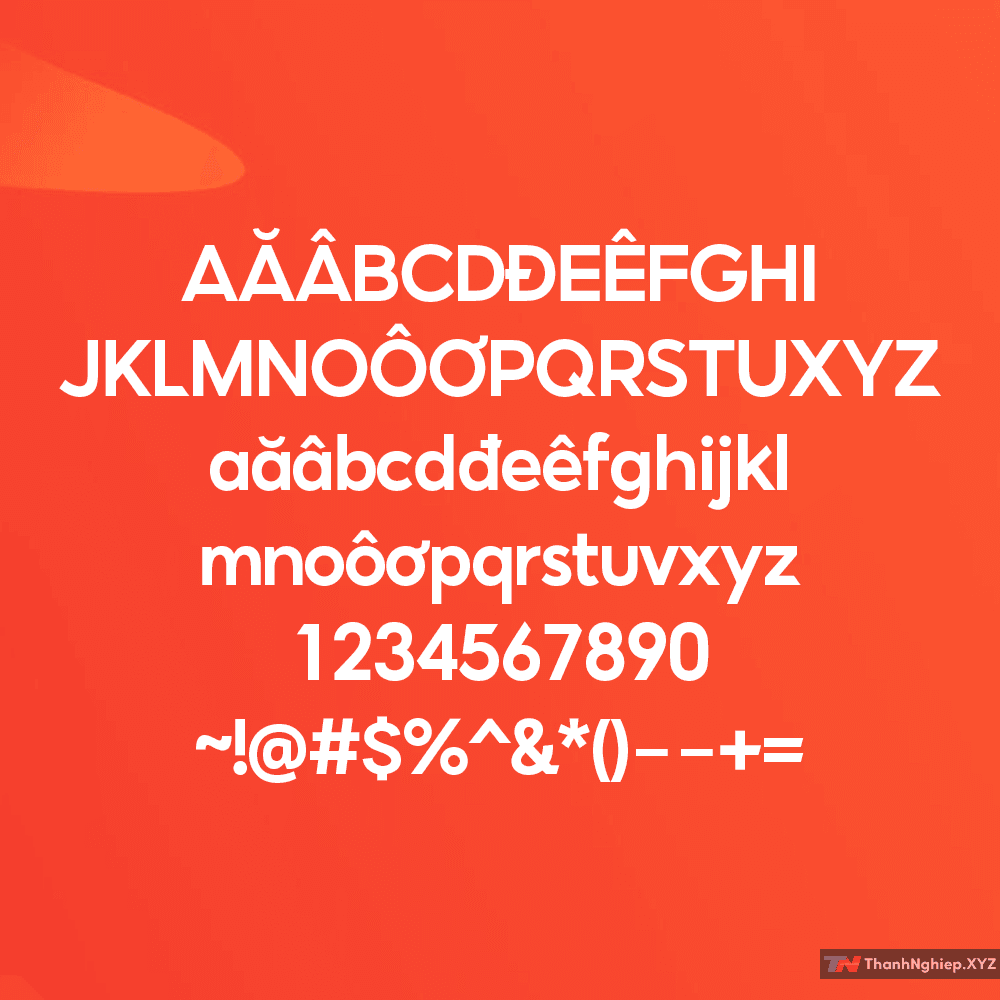
Bạn có bao giờ lướt Shopee và tự hỏi: “Ủa, sao font chữ trên app nhìn bắt mắt dữ vậy ta?” Bí mật chính là bộ Shopee Display & FVH Shopee Text – một combo font cực chất, giúp mọi thiết kế của bạn trông chuyên nghiệp, hiện đại và đúng chuẩn thương hiệu Shopee. Và tin vui là nó đã được Việt hóa hoàn chỉnh, tha hồ mà sáng tạo!
Bộ font Shopee gồm những gì?
Shopee Display – Sang, xịn, nổi bật
Bộ font Shopee Display được thiết kế theo phong cách sans-serif, vừa tối giản vừa tinh tế, giúp nội dung hiển thị rõ ràng, dễ đọc và cực kỳ thu hút. Nó bao gồm 5 biến thể:
- Shopee Display Light – Thanh thoát, dịu dàng, thích hợp cho nội dung phụ.
- Shopee Display Regular – Cân bằng, dễ đọc, dùng cho nội dung chính.
- Shopee Display Bold – Tăng độ nhấn mạnh, phù hợp với tiêu đề.
- Shopee Display ExtraBold – Đậm đà hơn, tạo điểm nhấn mạnh mẽ.
- Shopee Display Black – Cực dày, giúp nội dung nổi bật ngay lập tức.
FVH Shopee Text – Việt hóa chuẩn, đậm chất Shopee
- FVH Shopee Text Bold là phiên bản Việt hóa tối ưu, giúp thể hiện nội dung rõ ràng, không lỗi font, không mất dấu. Đặc biệt phù hợp với các tiêu đề, thông báo và banner quảng cáo.
Tại sao nên dùng Shopee Display & FVH Shopee Text?
1. Chuẩn Shopee – Chuyên nghiệp và hiện đại
Bộ font này được thiết kế riêng cho Shopee, mang lại cảm giác quen thuộc, thân thiện nhưng vẫn rất chuyên nghiệp.
2. Việt hóa hoàn chỉnh – Không lo lỗi font
Không còn cảnh “chữ mất dấu” hay “dấu lệch tông”, bộ font này đã được Việt hóa cẩn thận, hiển thị mượt mà trên mọi nền tảng.
3. Ứng dụng linh hoạt
- Thiết kế banner, poster, quảng cáo online – Tăng độ thu hút, giúp khách hàng “chốt đơn” nhanh chóng.
- Dự án thương mại điện tử – Phù hợp cho website, app bán hàng, giúp giao diện trở nên bắt mắt.
- Truyền thông thương hiệu – Nếu bạn đang làm marketing hoặc social media, đây là font lý tưởng để tạo sự đồng nhất.
Kết luận: Font cho dân bán hàng, xài là thích ngay!